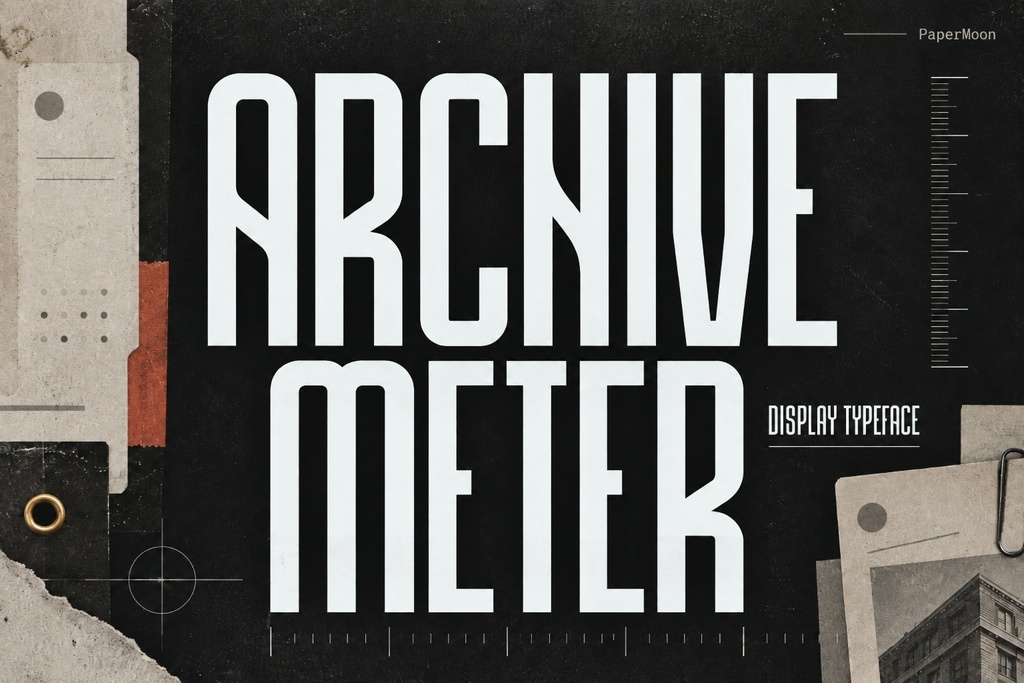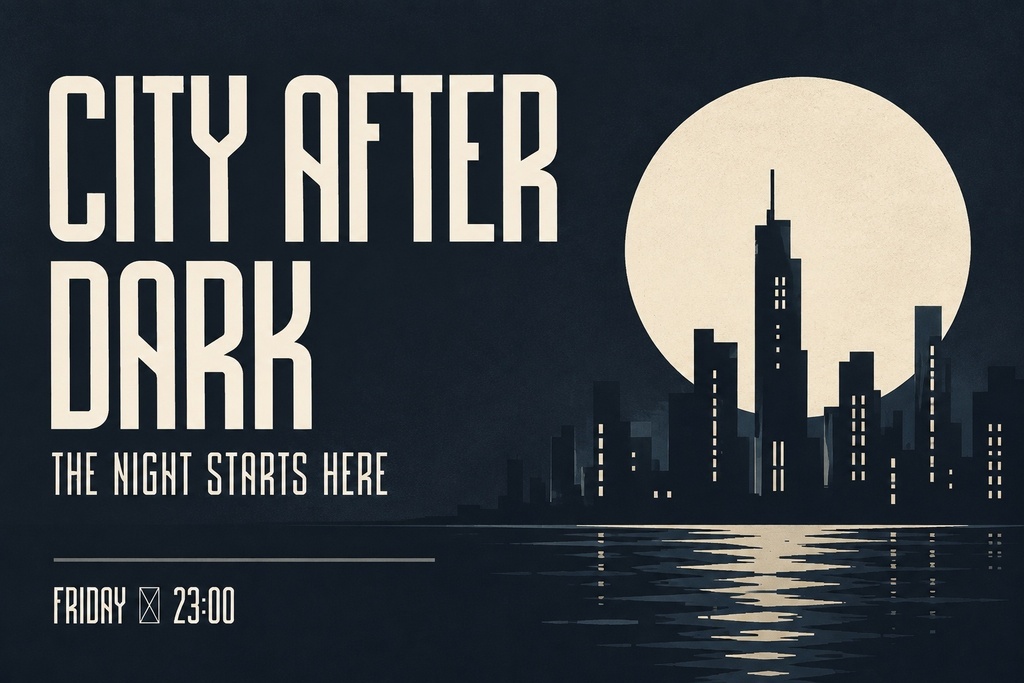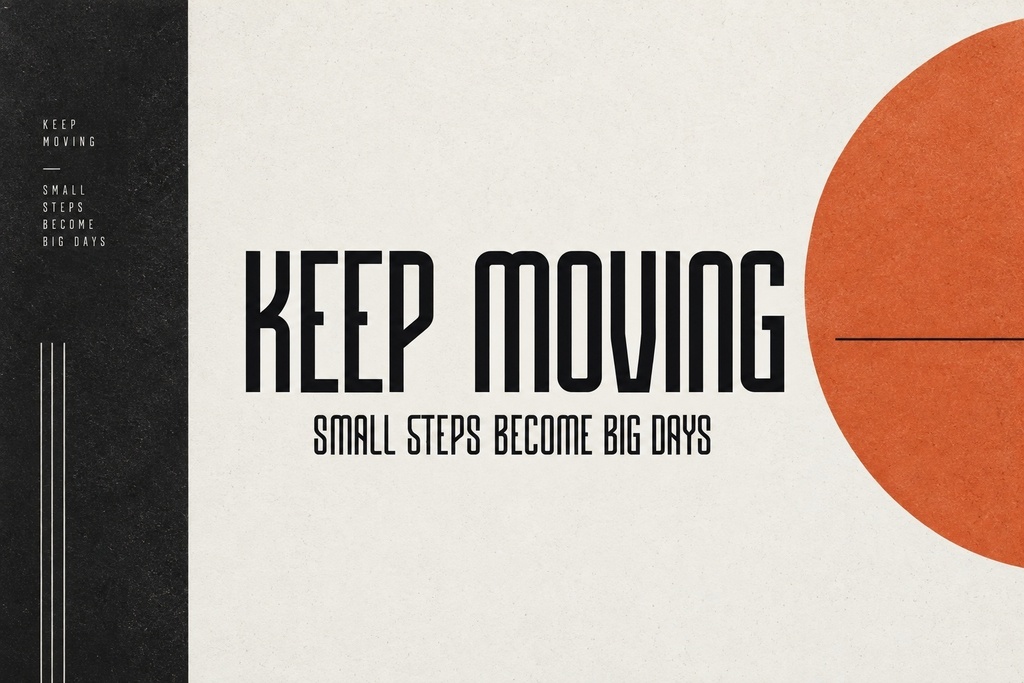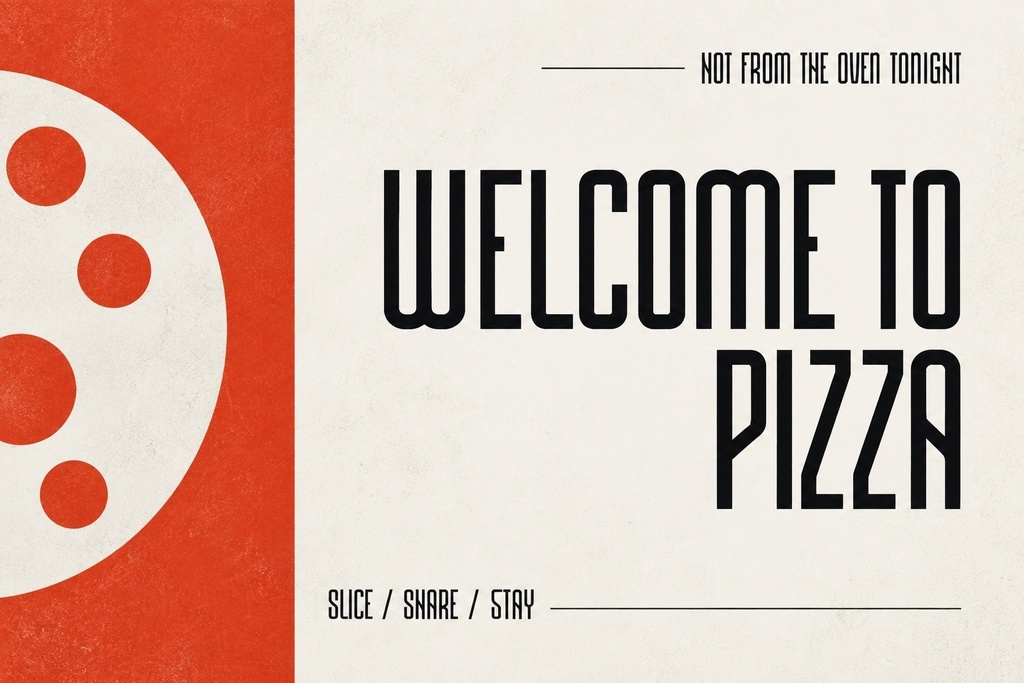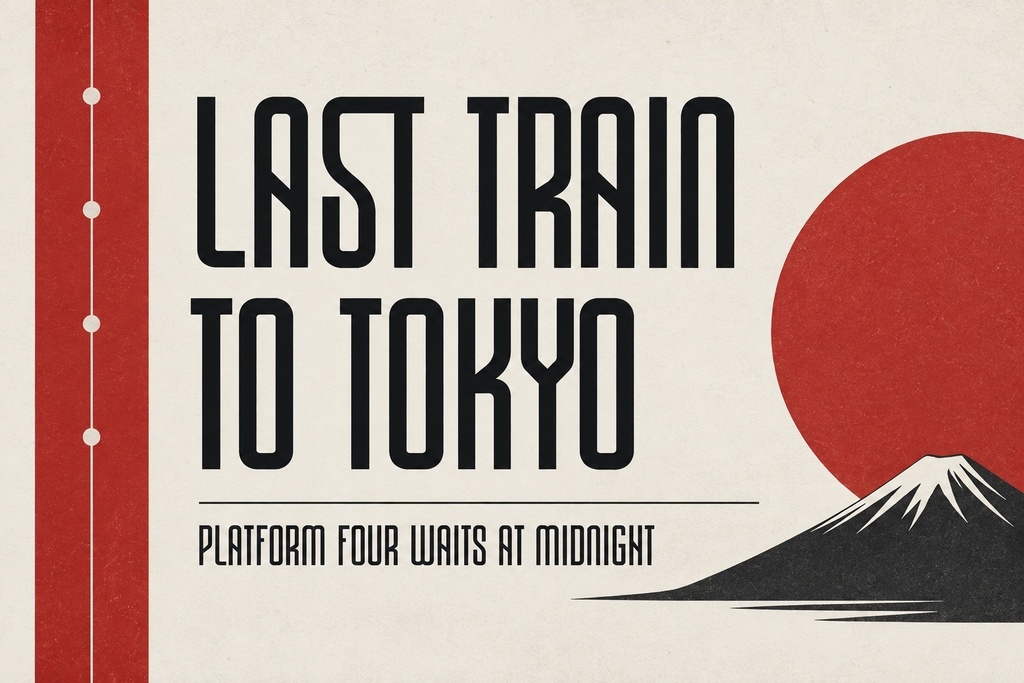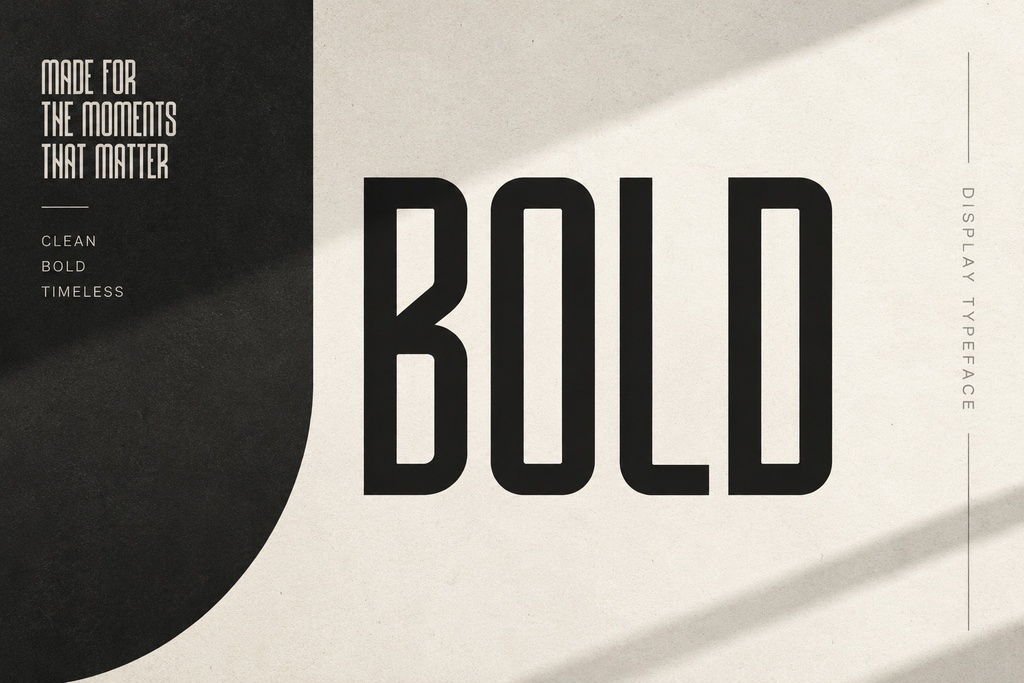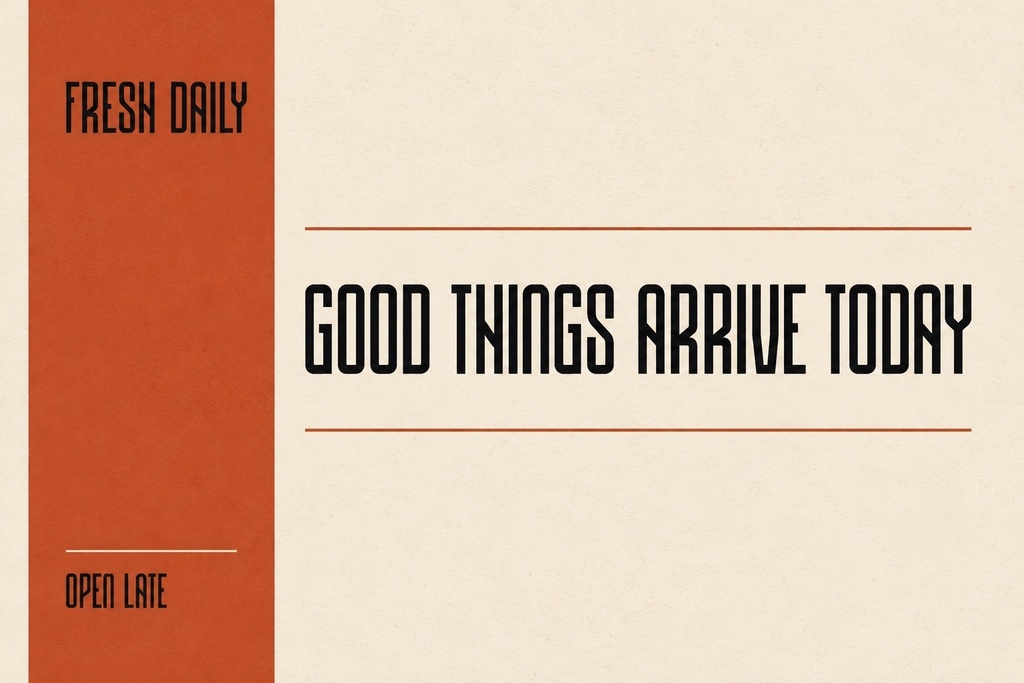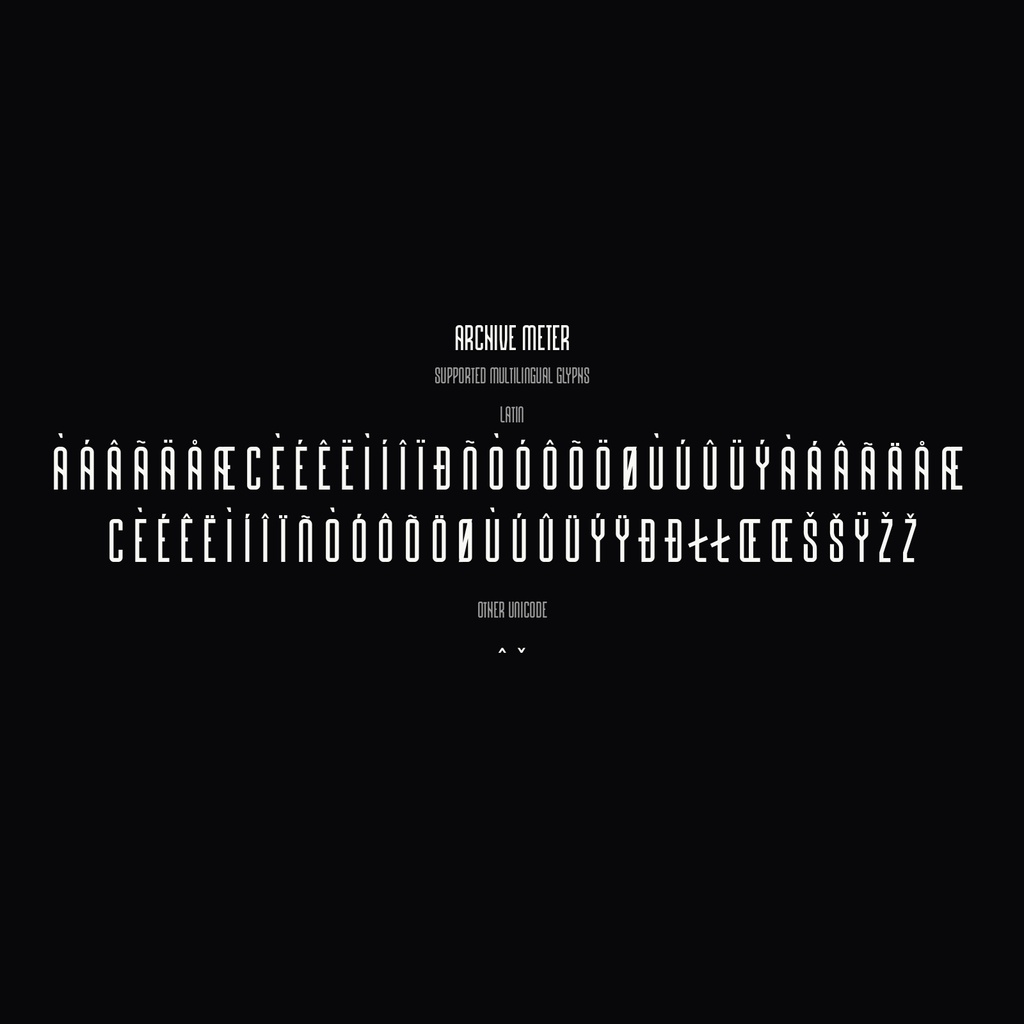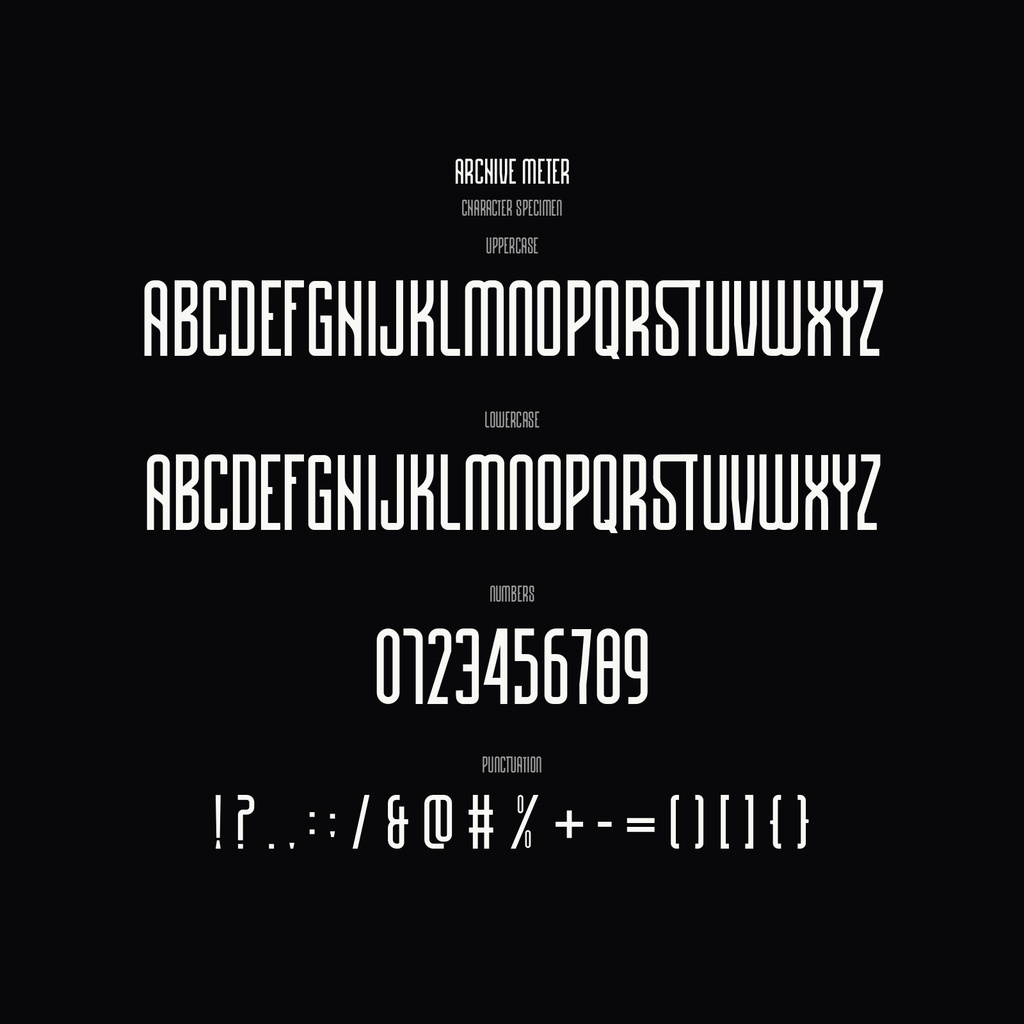
Archive Meter | シンプルでモダンなディスプレイフォント | ロゴ・ポスター・見出し向け
Archive Meterは、シンプルでモダンな存在感を添えるディスプレイフォントです。ブランドロゴやポスター、見出しを、クリーンな線と力強い形で印象的に仕上げます。 すっきりした構成の中に、視線を引きつける特徴的なディテールを備えています。洗練された印象と大胆な表情を両立し、文字を主役にしたビジュアルデザインに向いています。 収録内容 Archive Meterのフォントデータ。同梱内容とファイル形式は要確認です。 対応文字 多言語対応で、より多くのグリフを収録しています。対応言語、文字種、収録グリフの詳細は要確認です。 用途 ブランドづくり、ロゴ、ポスター、見出し、グラフィックデザインなど、文字を目立たせたい表現にご利用いただけます。対応範囲の詳細は販売時の案内をご確認ください。 形式 ファイル形式は要確認です。OTF、TTF、WOFF、WOFF2の収録有無は販売時にご確認ください。 対応環境 ご利用のソフトウェアが収録形式に対応しているか、購入前にご確認ください。対応アプリケーションとインストール方法は要確認です。 利用許諾 商用利用と個人利用の条件、再配布、転売、埋め込み、テンプレート利用の可否は、販売時のライセンス記載をご確認ください。具体的な許諾範囲は要確認です。 バージョン情報 バージョンと更新内容は要確認です。